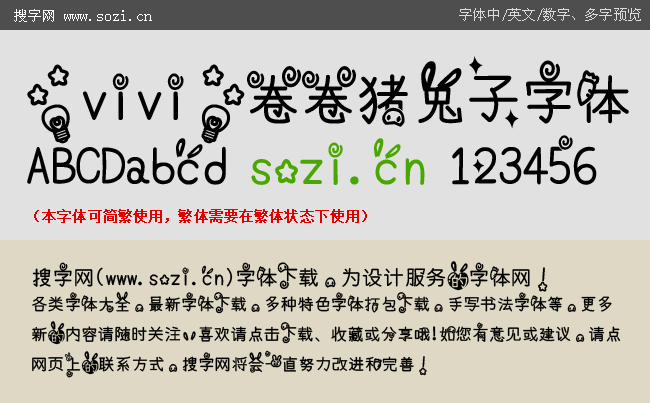
卷卷豬兔子字體
搜字網(wǎng)給大家提供一款卡通手寫風(fēng)格的手機(jī)中文字體下載。名字叫卷卷豬兔子字體,這款手機(jī)字體是仿照兒童手寫風(fēng)格的卡通手寫字體,結(jié)構(gòu)帶有POP字體風(fēng)格,字體間還插入了大量有趣卡通圖案,特別適合喜歡手機(jī)字體個性一些的朋友在手機(jī)上安裝使用。